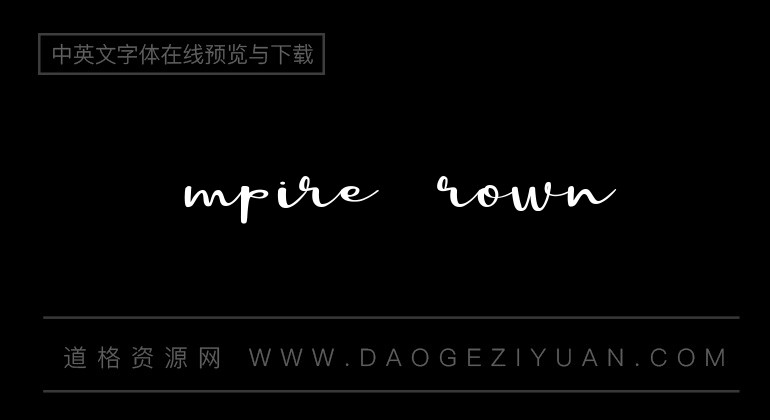
Empire Crown
Empire Crown 字体是一款源自20世纪30年代的老式英文字体,具有古典优雅的外观,其主要特点是英文字母采用圆润的曲线,字体的笔画粗细变化细腻,每一个字母都有自己的特点,使得字体的视觉效果非常出色。 Empire Crown 字体适合用于宣传海报、名片、书籍封面、海报、标志等设计,也可以用于文本的排版,具有经典的外观和良好的可读性,可以为您的设计提供更多的灵活性。
Empire Crown是一款非常不错的手写艺术字体,具有很好的视觉感,适合于文化类的宣传设计、商业类品牌的广告和产品包装设计以及个性化文字排版等较多场景。